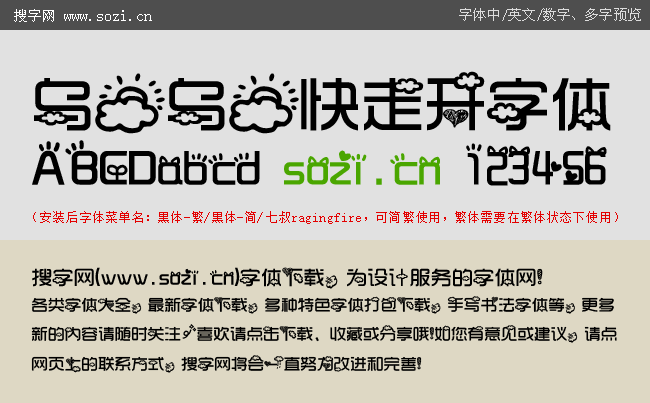
烏云烏云快走開字體
搜字網(wǎng)提供一款烏云烏云快走開字體手機中文字體下載,這款字體是以時尚中黑體為原形,個別文字和筆畫以及標(biāo)點被替換成了可愛的卡通圖形,時尚中黑字體整體字形筆畫均衡,風(fēng)格現(xiàn)代,字體方中帶圓,端莊雅致,簡約時尚。適宜喜歡卡通風(fēng)格的朋友下載使用。